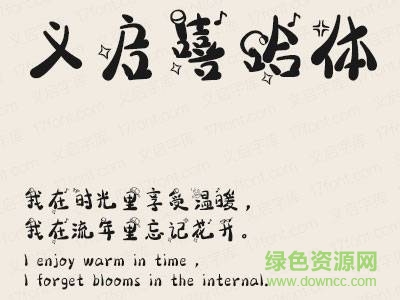
義啟嘻哈體字體
義啟嘻哈體是一款義啟出字體品的搞怪字體,嘻哈風(fēng)滿滿,想起童年的夢想,年少的時光,帶你回到最初,體驗真摯的情感。還等什么,快來綠色資源網(wǎng)下載使用!
義啟嘻哈體
義啟嘻哈體,那些年 她們還不懂什么裝扮 只一味涂抹笑顏;那些年 他們還不懂什么嘻哈 只一味擺凹造型;那些年的我們 早已各奔東西;誰還記得最初玩過的音樂,追逐過的夢想?義啟嘻哈體,帶你回歸本真。